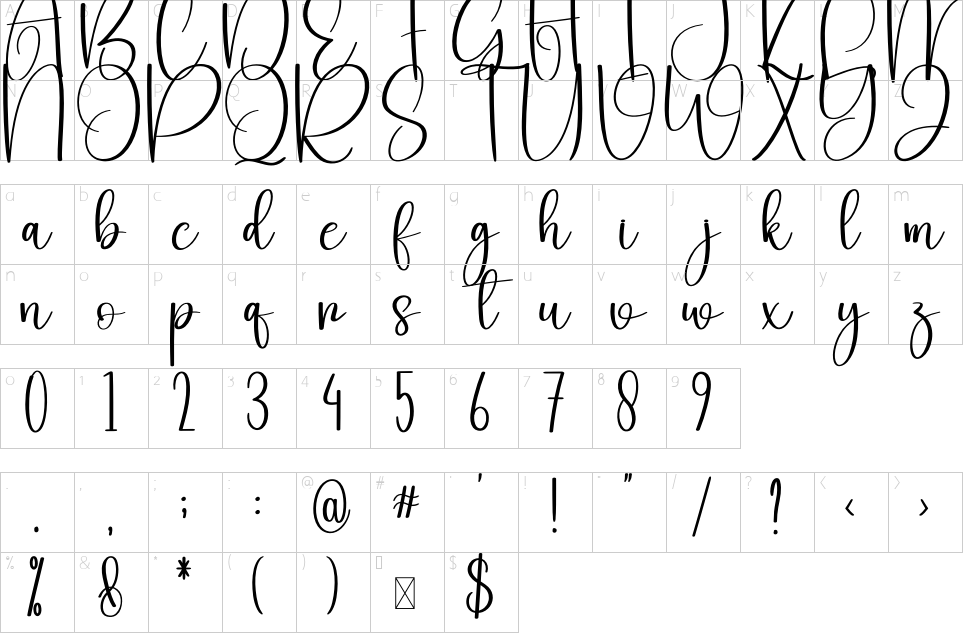
Descubra a autêntica essência da escrita com a Autography font. Desenvolvida por scratchones, esta elegante fonte oferece uma experiência única para criar e editar textos de maneira atraente e natural. As linhas finas e os traços suaves da Autography tornam cada palavra um ato de arte. Com seu design cuidadosamente pensado, a fonte é perfeita para projetos de design, seja para fins pessoais ou profissionais. Oferecida gratuitamente tanto para Windows quanto para Mac, a Autography font se destaca por sua facilidade de uso e estilo único. Descubra o poder da escrita com a Autography font e adicione uma nova dimensão de elegância a seus trabalhos.